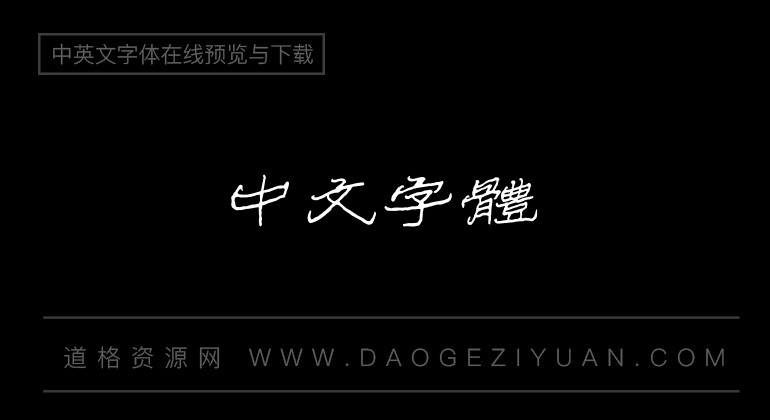
腾祥铁山硬隶繁
腾祥铁山硬隶繁字体是一款由腾祥字体工作室设计的汉字字体,它以铁山硬隶字体为设计基础,结合现代科技手段,采用汉字行书、行楷、隶书三种字体的特点,结合网页设计的特点,精心设计出一款兼容性极强的汉字字体,并且拥有极强的美感性,能够在网页设计中突出文字美感,使得网页设计更加精致。
腾祥铁山硬隶繁是一款非常不错的手写艺术字体,具有很好的视觉感,适合于文化类的宣传设计、商业类品牌的广告和产品包装设计以及个性化文字排版等较多场景。